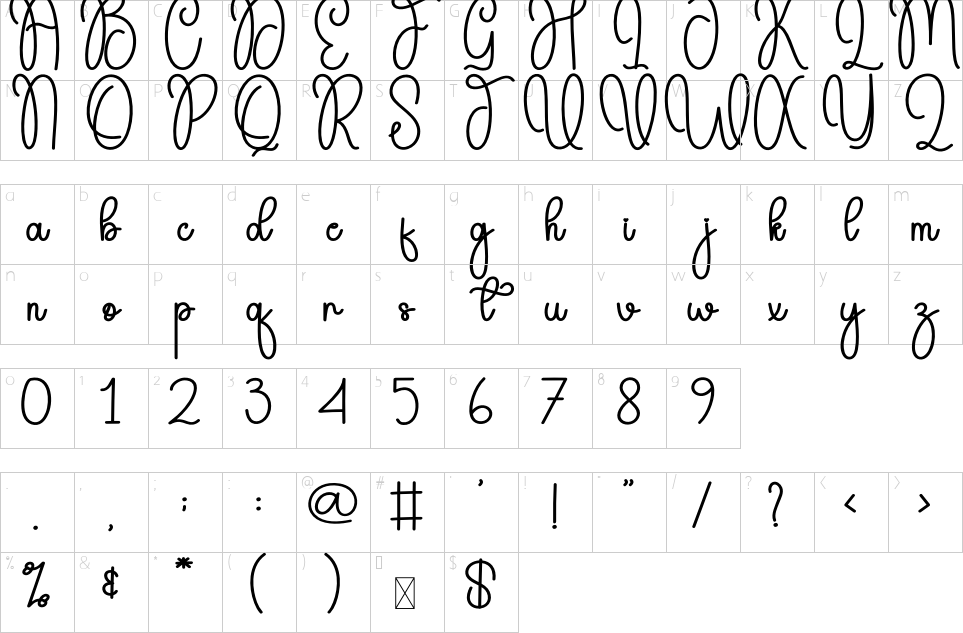
Delightful Font
Descubra Delightful Font, uma elegante e versátil escolha para designers que valorizam a simplicidade do bom design. Desenvolvida por William Jhordy, esta fonte oferece um toque de alegria em qualquer projeto gráfico. Com seu charme natural e arquitetura minimalista, Delightful Font é ideal tanto para o design de sites quanto para textos pessoais em sua maleta de ferramentas. Sua facilidade de uso e vasta gama de estilos garantem que Delightful seja uma opção confiável para qualquer designer buscando manter seu projeto limpo e alegre. Com um design simples mas profundo, Delightful Font é perfeito tanto para projetos pessoais quanto corporativos, prometendo um toque amigável em cada projeto onde for usada. Recomendado para designers que valorizam uma solução de fontes gráficas simples e agradável aos olhos. Se você está procurando por uma fonte gratuita para seus trabalhos, Delightful Font é uma ótima escolha.
Mapa de caracteres da fonte Delightful Font